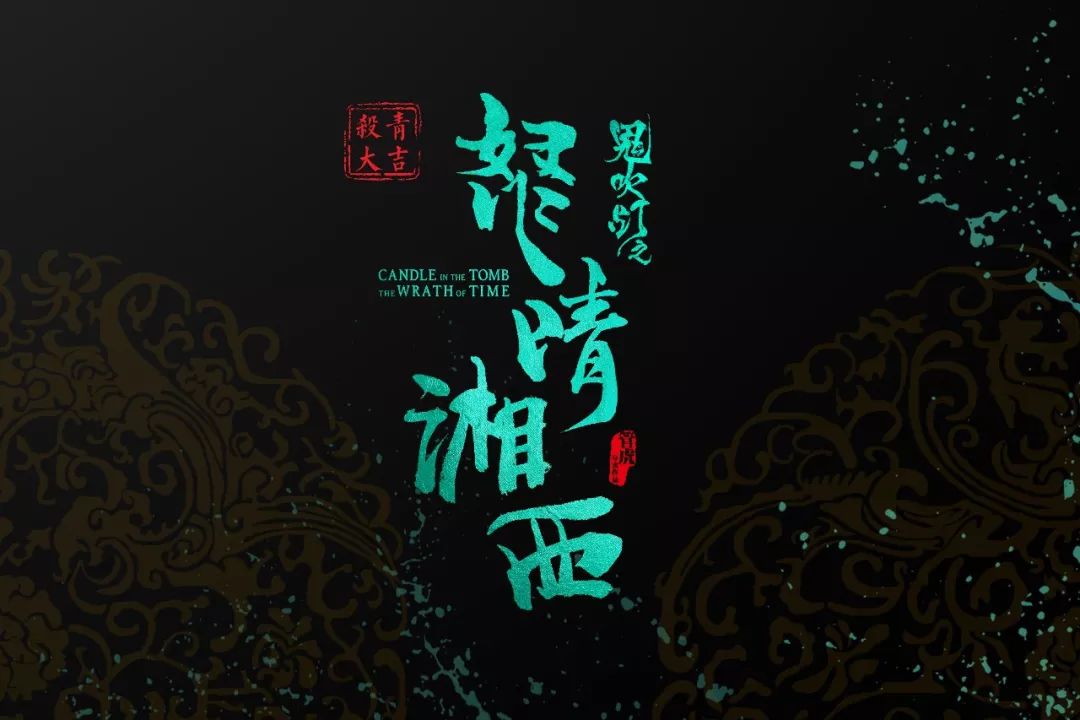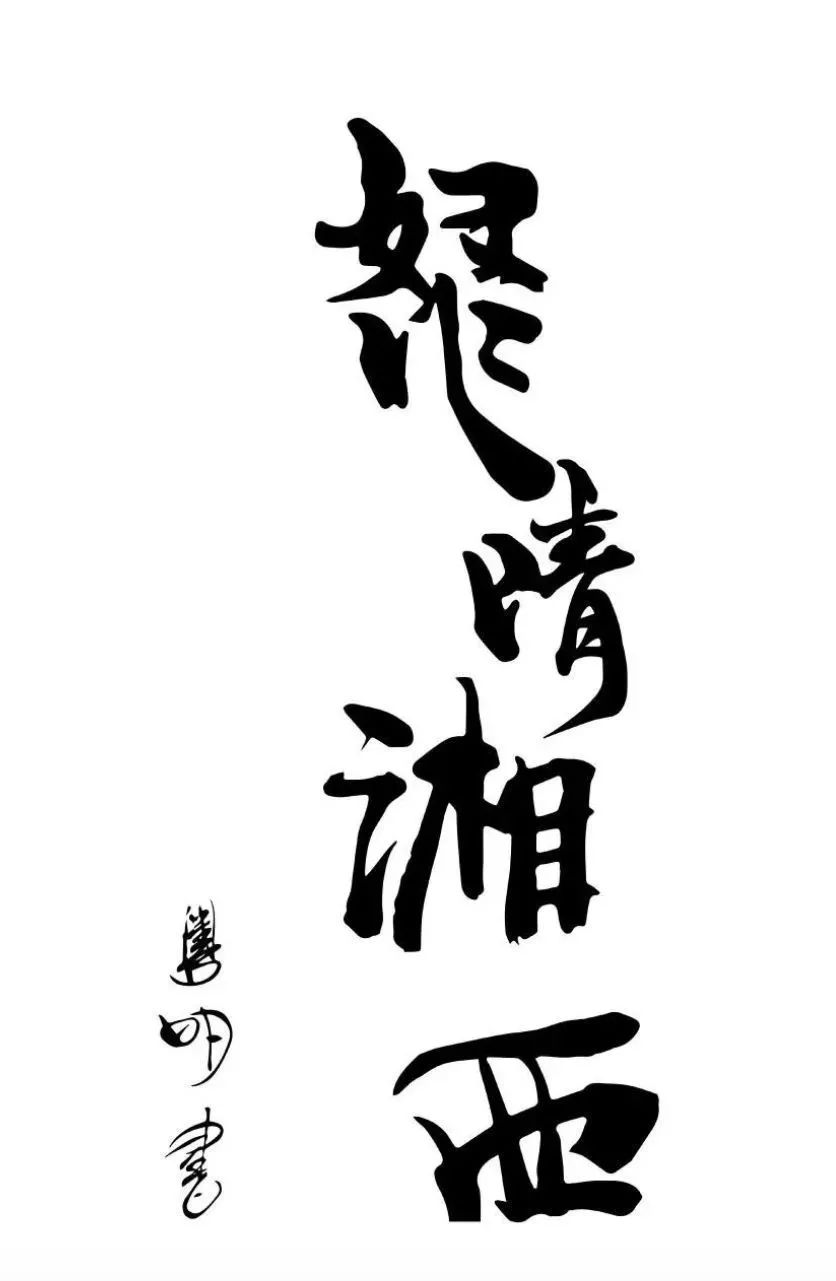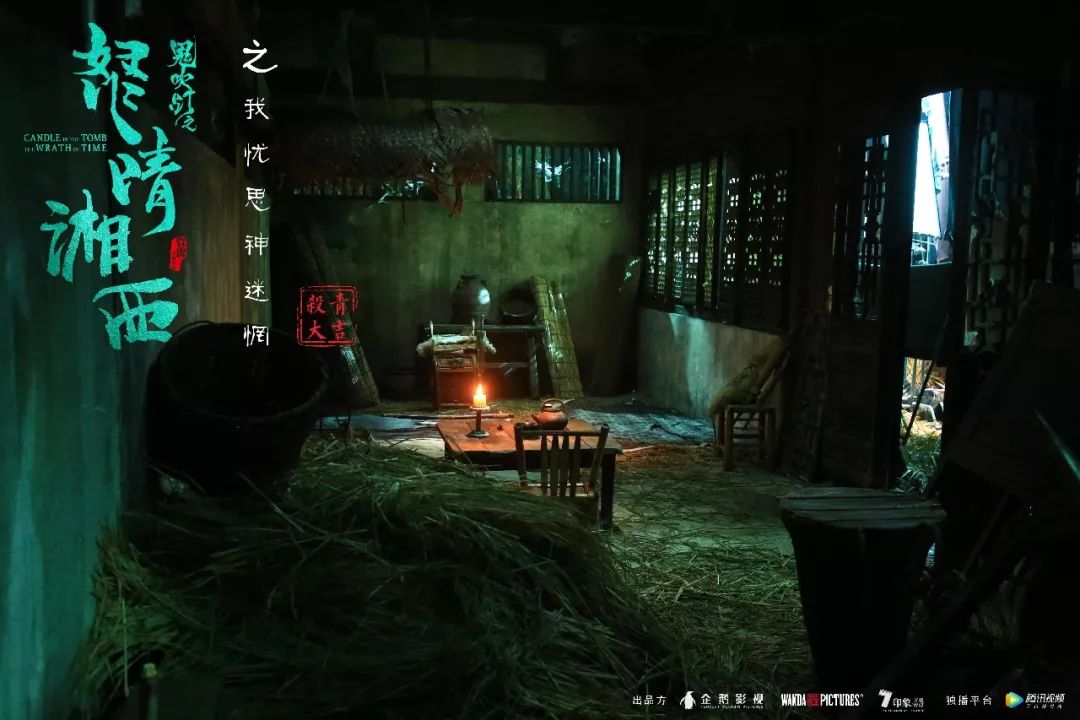
扮得了“柯南”,唱得了“片尾”,连“怒晴湘西”四个字都是他写的……
熟悉柚子的都知道,鬼吹灯系列一直是我的最爱,只不过拍了那么多,豆瓣评分高于7分的,屈指可数。
而最近有一部,才播出6集,就高达8.3,不用说,你也猜到了,就是《怒晴湘西》。
要说这剧为啥好,除了管虎监制,最大的亮点就是潘粤明了,多少人等着他的《白夜追凶2》呢?
不过这次他扮演的卸岭魁首陈玉楼,就是胡八一身边那个神神叨叨算命的老头陈瞎子……
演技自然不用说,为了让人物形象更加鲜明,扇子、帽子,还有那上了热搜的LED小眼镜,都用了心。
除此之外,创意策划也有他,片尾曲也是他……
还是多才多艺的摄影师(就问还有什么是你不会的)。
难怪被网友们封为“宝藏大叔”,不过这还不是最令人拍案叫绝的,“怒晴湘西”那四个字,都是他写的!!!
什么,不信?看这里:
信了吧,关键人家还用鬼吹灯的方式,表达谦虚,请收下我的膝盖~
确实这个有点文艺气息的书法体,也很符合湘西的风情,在网上收获了一众好评。
还带动了影迷的书法热潮。
不过这可不是一时头脑发热,翻看潘老师的微博,就会理解了~
正如网友所说,喜欢一个明星,不仅仅是剧里的角色,还有戏外的人格魅力。
最后让我们跟着陈总把头,提高一下海报的审美吧~